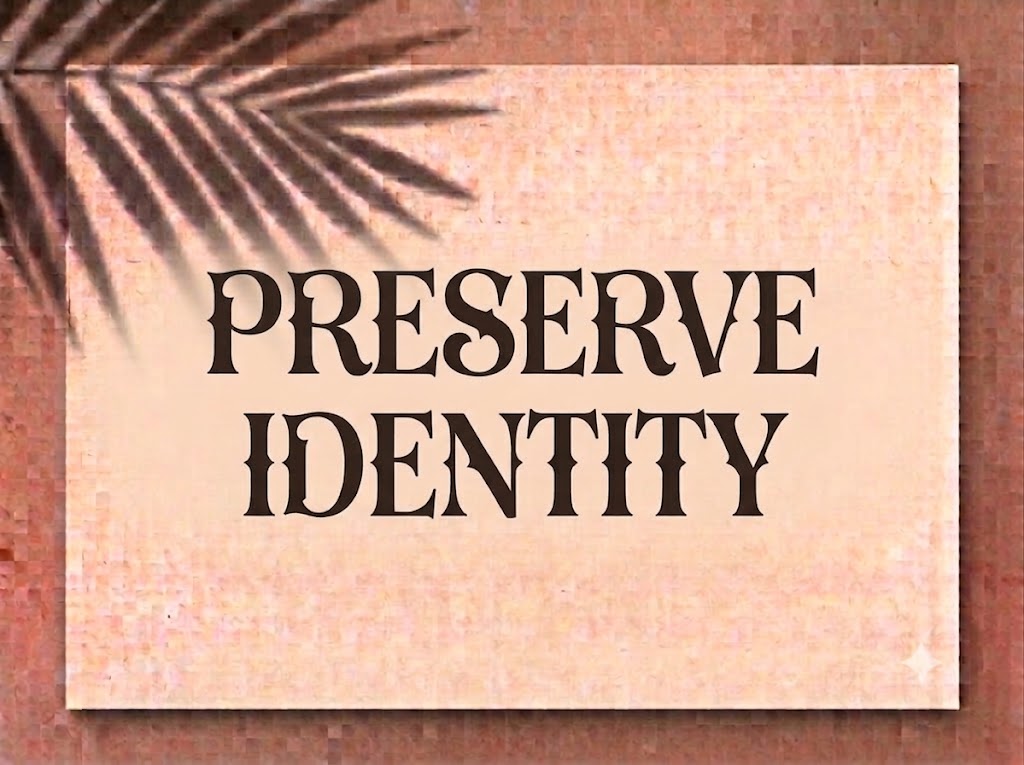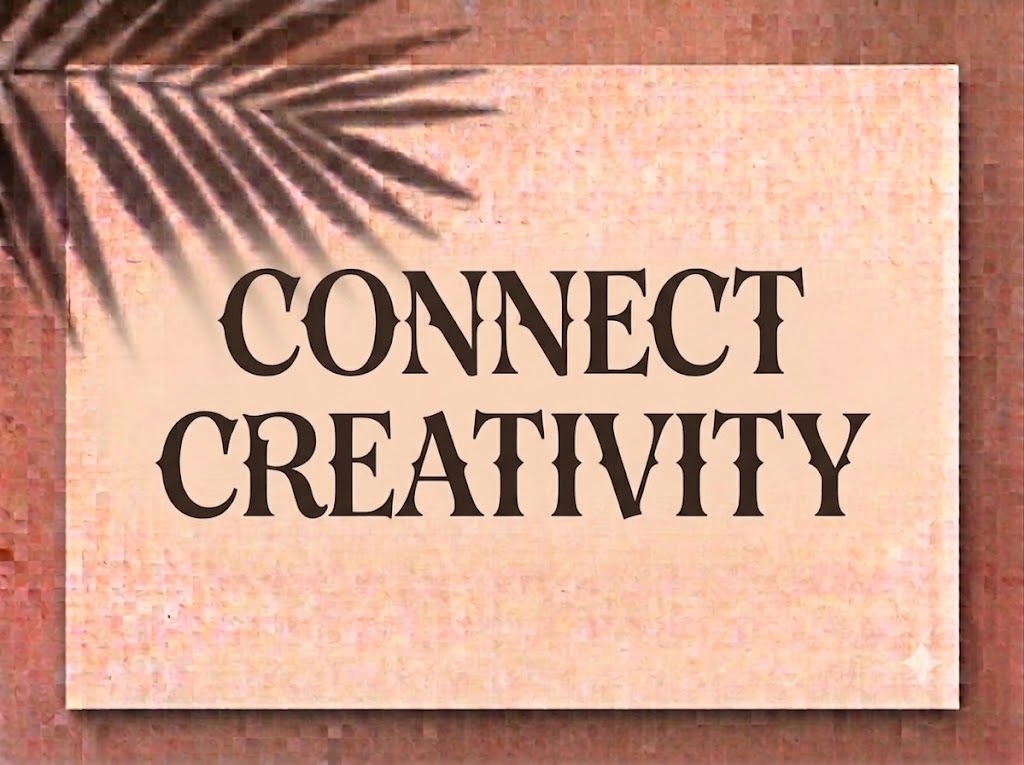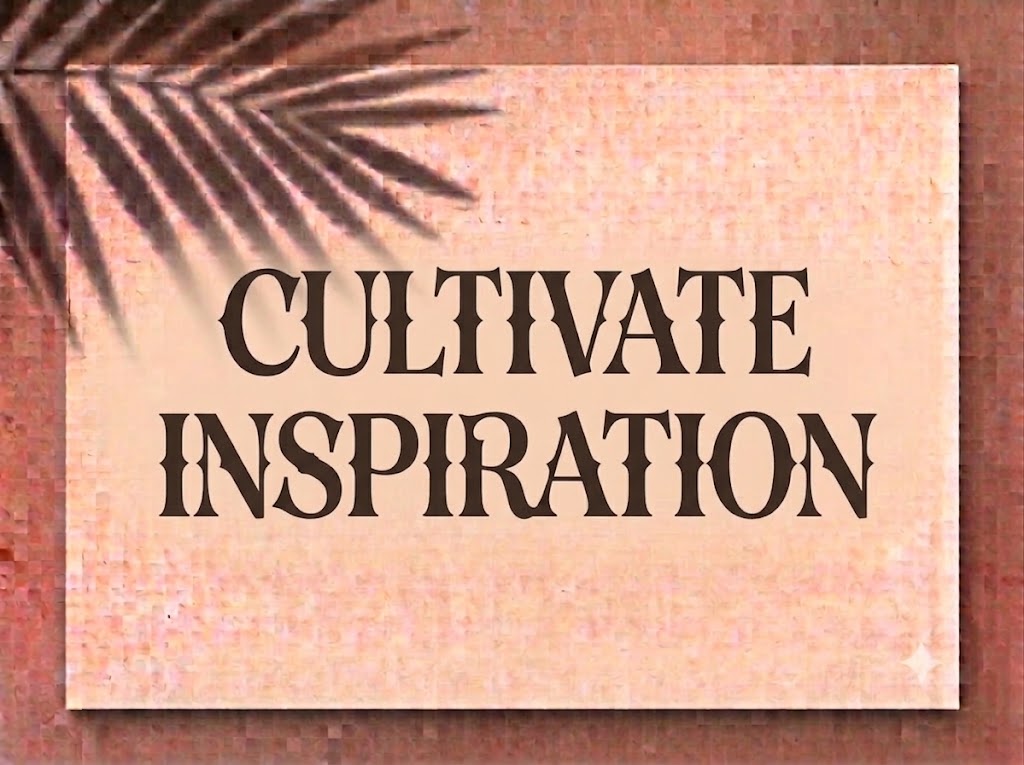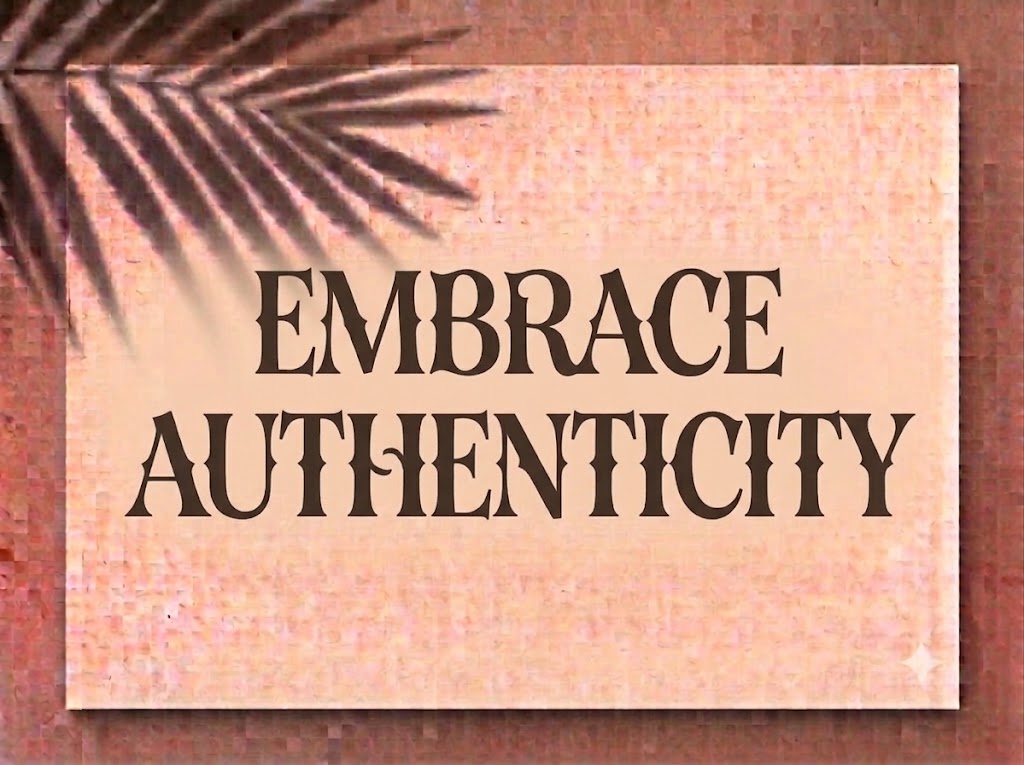
1FTV Trepang
Trong giới thiết kế đồ họa và sản xuất nội dung hình ảnh cao cấp, việc lựa chọn một phông chữ Serif vừa mang vẻ uy nghi cổ điển, vừa có những đường nét biến điệu sắc sảo luôn là chìa khóa để định hình giá trị thương hiệu. Những phông chữ này giúp các dòng tiêu đề thoát khỏi sự nhàm chán thông thường, mang lại hơi thở thời trang, kiêu kỳ và đầy tính nghệ thuật.
Nếu bạn đang tìm kiếm một phông chữ hiển thị có chân độc đáo để nâng tầm thiết kế bìa lookbook, nhận diện thương hiệu phân khúc cao cấp hay làm tiêu đề video ngắn thu hút, thì font 1FTV Trepang chính là sự lựa chọn không thể bỏ qua.
Giới thiệu về font 1FTV Trepang
Font 1FTV Trepang là một bộ chữ hiển thị có chân (serif display) mang phong cách tân cổ điển đầy quý phái, thanh lịch và hướng đến các tiêu chuẩn mỹ thuật tinh tế.
Đặc điểm nổi bật của phong cách thiết kế Trepang
Sức hút lớn nhất của font 1FTV Trepang đến từ sự kết hợp tài tình giữa phom dáng chữ đứng kiêu sa và các chi tiết vát nhọn nhẹ nhàng ở đầu nét:
Tỷ lệ nét chữ cân đối: Độ tương phản giữa nét thanh và nét đậm được tính toán vừa phải, mang lại cảm giác thoáng đãng.
Hỗ trợ bộ chữ hoa và thường đồng bộ: Khác với nhiều phông chữ display chỉ hỗ trợ chữ in hoa.
Hệ thống khoảng cách chữ (kerning) và độ giãn dòng được căn chỉnh chuẩn xác đến từng pixel.
Tích hợp đầy đủ bộ chữ cái hoa – thường, dãy chữ số từ 0-9 dáng đứng thanh lịch cùng hệ thống các ký tự đặc biệt, dấu câu thông dụng.
Hình ảnh demo thực tế của font 1FTV Trepang
Kích thước nhỏ (12pt – 24pt): Nhờ cấu trúc chữ đứng và khoảng hở nội tại thông thoáng.
Kích thước lớn (36pt – 72pt): Đây là đất diễn lý tưởng nhất để font phô diễn toàn bộ sự kiêu sa.
Ứng dụng của font Trepang trong thiết kế đồ họa và làm video
Sở hữu nét cá tính sang trọng, quý phái và cấu trúc hoa – thường linh hoạt, font 1FTV Trepang mở ra không gian ứng dụng rộng lớn cho các dự án truyền thông hiện đại:
Làm tiêu đề cho video ngắn (TikTok, Reels, Shorts): Kiểu chữ serif thanh lịch này hiển thị vô cùng ấn tượng trên các khung hình đứng tỷ lệ 9:16 của thiết bị di động.
Thiết kế bìa tạp chí, Lookbook và Poster nghệ thuật: Hoàn hảo cho các ấn phẩm truyền thông thuộc lĩnh vực thời trang xa xỉ, mỹ phẩm cao cấp, trang sức.
Ảnh thu nhỏ mạng xã hội : Vũ khí tuyệt vời để tạo nên những chiếc thumbnail YouTube, TikTok mang tính nghệ thuật cho các vlog chữa lành, làm đẹp, e-commerce thời trang nhằm nâng cao tỷ lệ nhấp chuột.